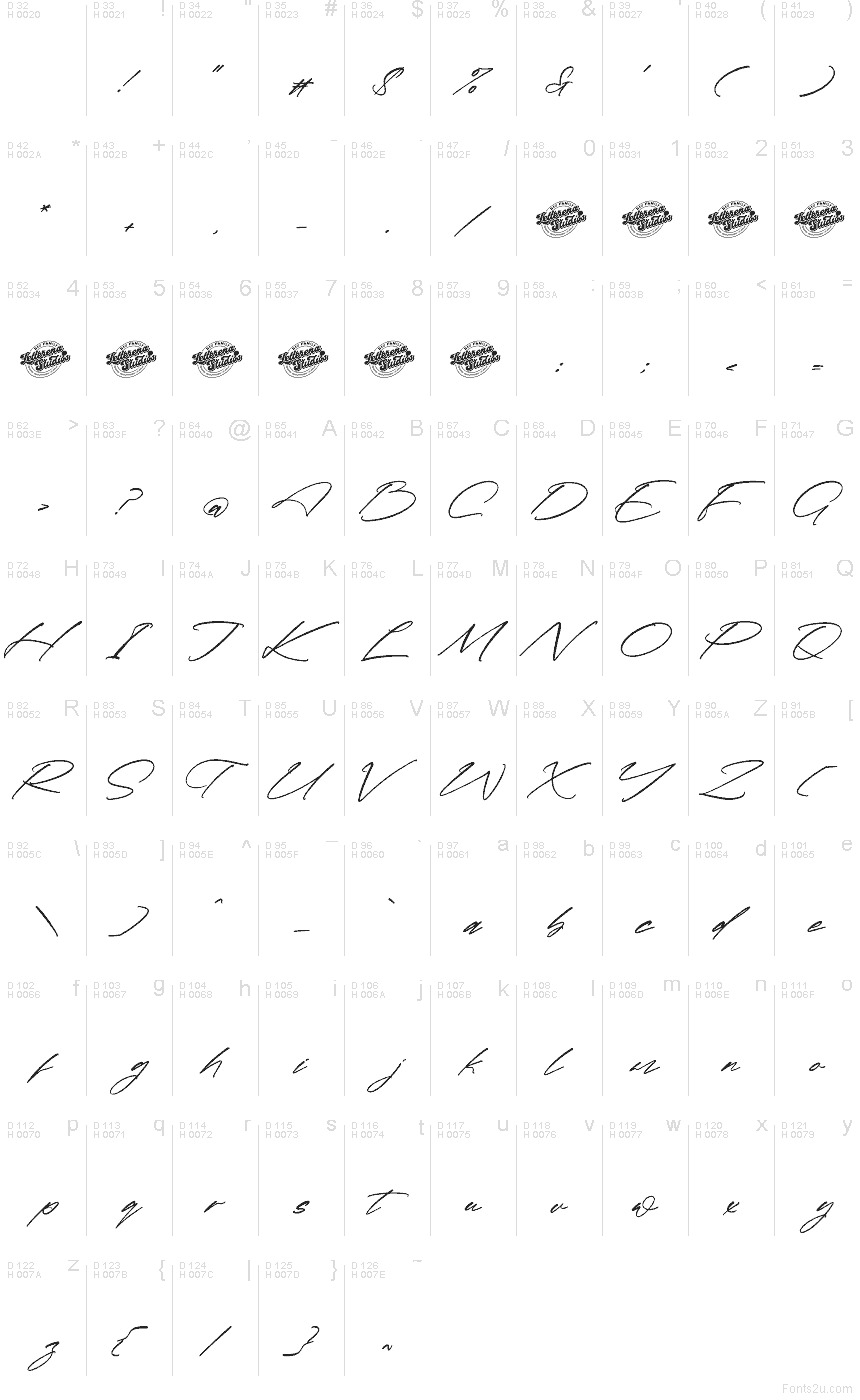
Terrycotta, autorstwa Letterena Studios, to darmowy odręczny krój pisma, który nadaje tekstowi charakter osobistego podpisu. Litery układają się lekko i płynnie, łącząc smukłe pętle z szybkimi, pociągnięciami przypominającymi ruch pędzla, dzięki czemu font wygląda naturalnie i autentycznie, a nie sztywno czy sztucznie.
Doskonale pasuje do brandingu, opakowań kosmetyków, butikowej papeterii, cytatów w social mediach czy nagłówków w magazynach, gdzie potrzeba tego „podpisanego” sznytu. Wykorzystaj go również w krótkich nagłówkach lub monogramach – wydłużone początki i końcówki liter sprawią, że nawet krótki napis będzie wyglądał jak projekt wykonany na zamówienie.